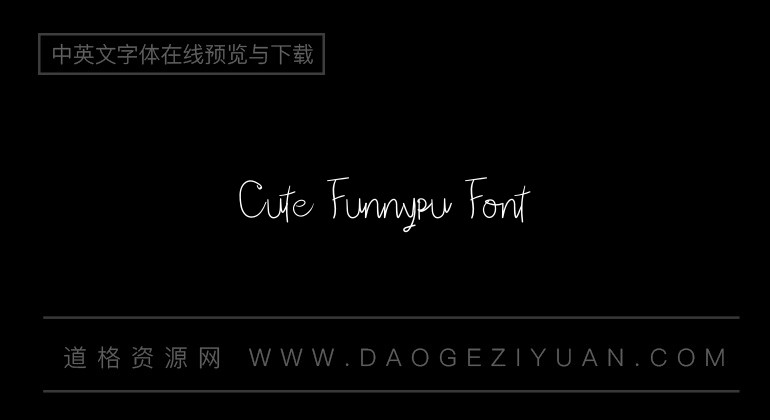
Cute Funnypu是一种可爱的手写风格字体,具有轻松和愉快的感觉,适用于许多不同类型的设计项目。 这种字体具有圆润的线条和明亮的颜色,使其非常适合用于儿童或青少年相关的设计,例如卡通、海报、广告、书籍和漫画等。 Cute Funnypu字体的字母形状和大小也非常统一,使得它易于阅读和识别。它还包括一些装饰性元素,例如星星、心形和花朵,可以用于添加额外的视觉吸引力。 总之,Cute Funnypu字体是一个有趣、可爱、轻松的字体,适合用于各种类型的设计项目。内容介绍
Cute Funnypu Font是一款非常不错的手写艺术字体,具有很好的视觉感,适合于文化类的宣传设计、商业类品牌的广告和产品包装设计以及个性化文字排版等较多场景。